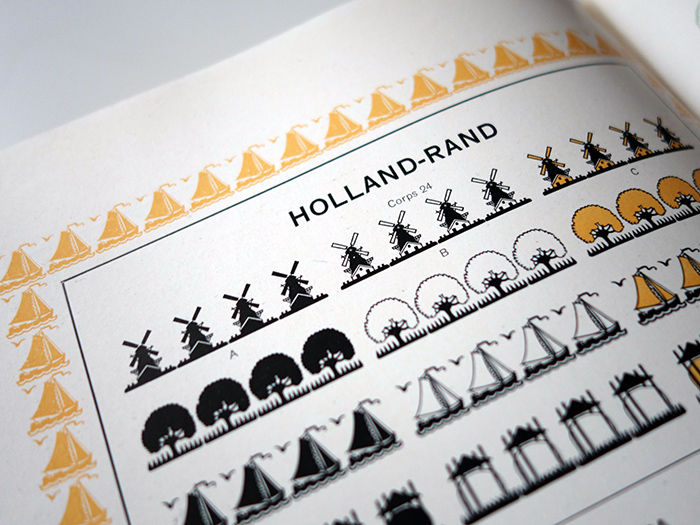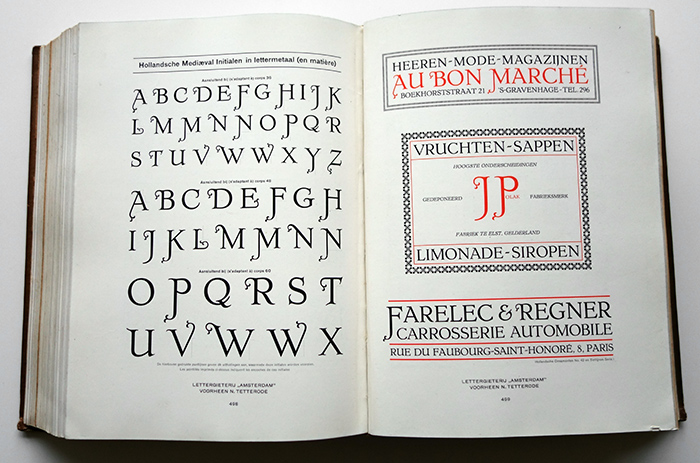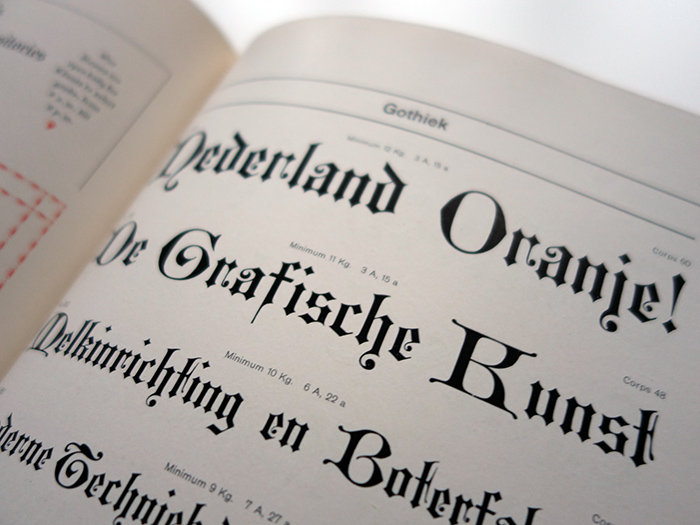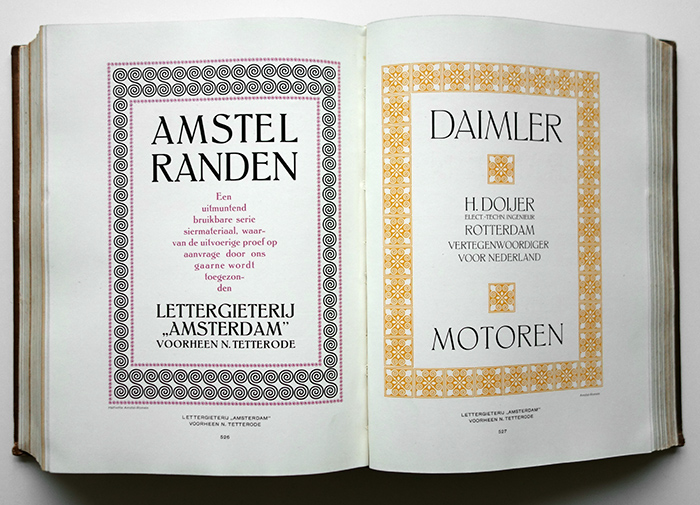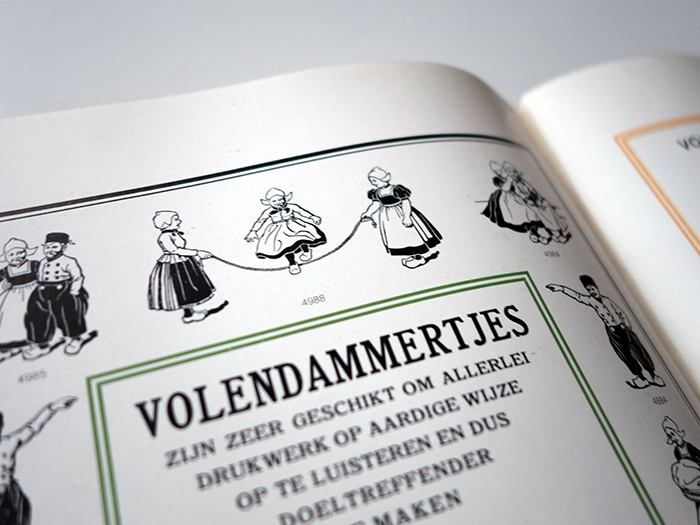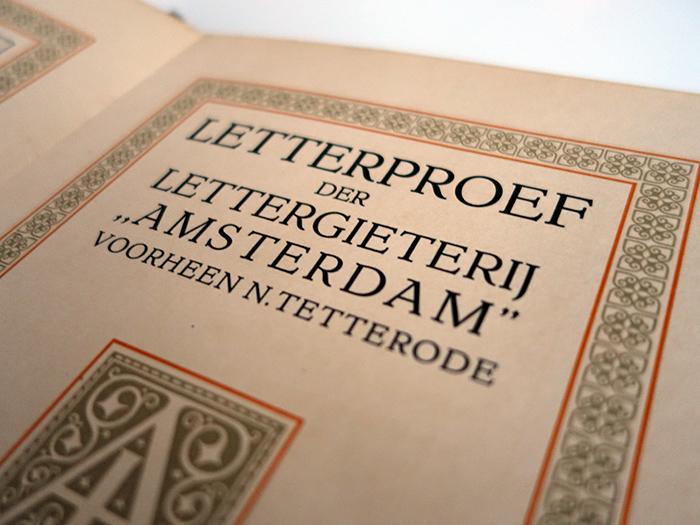
Ursprünglich von Nicolaas Tetterode in Rotterdam gegründet, wurde diese Gießerei später nach Amsterdam verlegt und firmierte dann als N.V. Lettergieterij »Amsterdam« vorheen N. Tetterode. Die Gießerei wurde 1988 geschlossen. Bleisatzmaterialien gingen an Fundición Tipográfica Neufville in Barcelona.
Das hier vorliegende Buch ist die Hauptprobe von 1916. Nachfolgend das Inhaltsverzeichnis:
- Accolades (Koperen)
- Accolades (Specie-)
- Advertentie-Randen
- Advertentie-Randen (2e Serie)
- Advertentie-Randen (3de Serie)
- Advertentie-Randen (Moderne), Serie 1–7
- Aldine Cursief (Vette)
- Aldine (Halfvette)
- Aldine (Verlegende)
- Adline (Vette)
- Algebrateekens
- Amstel-Cursief (Fantasieletter)
- Amstel-Randen
- Amstel-Romein (fantasieletter)
- Amstel-Romein (Halfvette)
- Annonce-Antieke
- Annonce-randen (Koperen)
- Antieke (Annonce-)
- Antieke (Breede Halfvette)
- Antieke (Breede Magere)
- Antieke (Breede Vette)
- Antieke (Compresse)
- Antieke Cursief (Halfvette)
- Antieke Cursief (Vette)
- Antieke (Kaart-)
- Antieke Kapitaaltjes (Breede Halfvette)
- Antieke Kapitaaltjes (Breede Magere)
- Antieke Kapitalen (Breede Halfvette)
- Antieke Kapitalen (Breede Magere)
- Antieke Kapitalen (Halfvette Kaart-)
- Antieke Kapitalen (Kaart-)
- Antieke Kapitalen (Omlijnde)
- Antieke (Omlijnde)
- Antieke (Royal-)
- Antieke (Smalle)
- Antieke (Smalle Halfvette)
- Antieke (Smalle Magere)
- Antieke (Smalle Vette)
- Antieke (Verlegende Vette)
- Antieke (Vette)
- Arabisch
- Artistica
- Aspectteekens
- Astronomische teekens
- Athenienne (Breede)
- Atlas-Randen
- Bataksch (Madaïlingisch)
- Bataksch (Toba)
- Belgische ordeteekens
- Beursletters
- Bilderdijk-Initialen
- Bilderdijk-Ornamenten
- Bilderdijk-Ornamenten (als rand)
- Bilderdijk-Vignetten
- Biljetletter (Cursief)
- Biljetletter (Romein)
- Blad-Versieringen
- Bloemrandjes
- Blok-Randen
- Boegineesch
- Boekletter (Corpsen-overzicht onzer)
- Boekletter (Serie-overzicht onzer)
- Boekletter (Toepassingen onzer)
- Boekletter (Overzicht breedte der)
- Boekletter met toepassing van vette letter
- Boek-Randen
- Boston-Schrift
- Botanische teekens
- Breede Cheltemham (fantasieletter)
- Breede Egyptische Cursief
- Breede Geschaduwte Italienne
- Breede Halfvette Antieke
- Breede Halfvette Antieke Kapitaaltjes
- Breede Halfvette Antieke Kapitalen
- Breede Magere Antieke
- Breede Magere Antieke Kapitaaltjes
- Breede Magere Antieke Kapitalen
- Breede Vette Antieke
- Breede Vette Antieke Kapitalen
- Breede Vette Cheltenham
- Breede Vette Egyptienne
- Breede Vette Romaansch
- Breukcijfers
- Capella
- Capella (Halfvette)
- Cheltemham (fantasieletter)
- Cheltenham (Breede) (fantasieletter)
- Cheltenham (Breede Vette)
- Cheltenham Cursief (fantasieletter)
- Cheltenham (Smalle Vette)
- Cheltenham (Vette) (fantasieletter)
- Chemische teekens
- Chineesch
- Chineesch, in verbinding met Japansch Káta-Kána
- Chineesch. Overzicht der 213 klassenhoofden
- Circulaire-Cheltemham
- Circulaire-Romaansch
- Circulaire- en Schrijfletters en Titelrekken
- Cirkels (Koperen)
- Clio
- Clio (Halfvette)
- Clio-Ornamenten
- Clio-Rand
- Columbia (Open)
- Columbia-Randen
- Columbia (Smalle)
- Cobinatielijnen (Koperen)
- Compresse Antieke
- Compresse Etienne
- Coptisch
- Corpsen-overzicht onzer boekletter
- Correspondentieteekens
- Costa-Ornamenten (Da)
- Coupon-Randen
- Coupon-Randen (Romania)
- Cijfermuziek
- Cijfers, Diverse (breukcijfers, onderstreepte cijfers, enz.)
- Cijfers (Doorgeslagen)
- Cijfers (Geazureerde)
- Cijfers in een cirkel
- Cijfers met streep er boven
- Cijfers (Onderstreepte)
- Cijferschrift (Makassaarsch en Boegineesch)
- Dampselfiguren
- Dienstregelingen (Materiaal voor)
- Dierenriemteekens
- Diverse (Tabelcijfers, koperen lijnen, teekens, enz.)
- Dollarteekens
- Doorgeslagen cijfers
- Duitsch
- Dutisch (Halfvette)
- Duitsch en Oostersche schriften
- Electa (fantasieletter)
- Egyptienne
- Egyptienne (Breede Vette)
- Egyptienne (Mediæval) (fantasieletter)
- Egyptienne (Vette Verlengde)
- Egyptische Cursief (Breede)
- Elegant, Serie 1
- Elegant, Serie 2
- Estrangelo (Syrisch)
- Etienne (Compresse)
- Etienne (Moderne)
- Etienne (Verlengde)
- Etienne (Vette Verlengde)
- Eureka
- Eureka-Rand
- Excelsior (Halfvette Schrijfletter)
- Excelsior (Schrijfletter)
- Fantasia
- Fantasia-Kapitalen
- Fantasieletter
- Fileten (Koperen)
- Firenze (fantasieletter)
- Vette Romaansch (Open)
- Vette Romaansch (Smalle)
- Vette Romaansch (Verlengde) (De Vinne)
- Vette Verlengde Egyptienne
- Vette Verlengde Etienne
- Vignetten (Bilderdijk-)
- Visite
- Volendammertjes
- Vrije Richting-Ornamenten
- Wetenschappelijke teekens
- Wiskundeteekens
- Wortelteekens
- Zebra
- Zwarte handen
- Zwart-Grijs-Randen